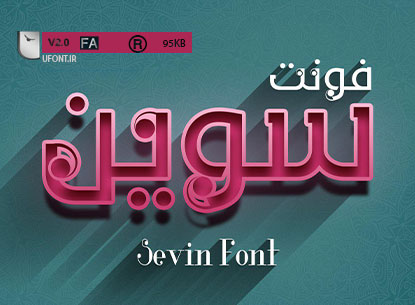
دانلود فونت فارسی سِوین
دانلود فونت فارسی سِوین ، فونت فارسی با ساختار پیچیده و تلفیق شده با عناصر اورنامنت که به واسطه درست بکار رفتن این عناصر بسیار یکدست و زیبا خروجی می دهد